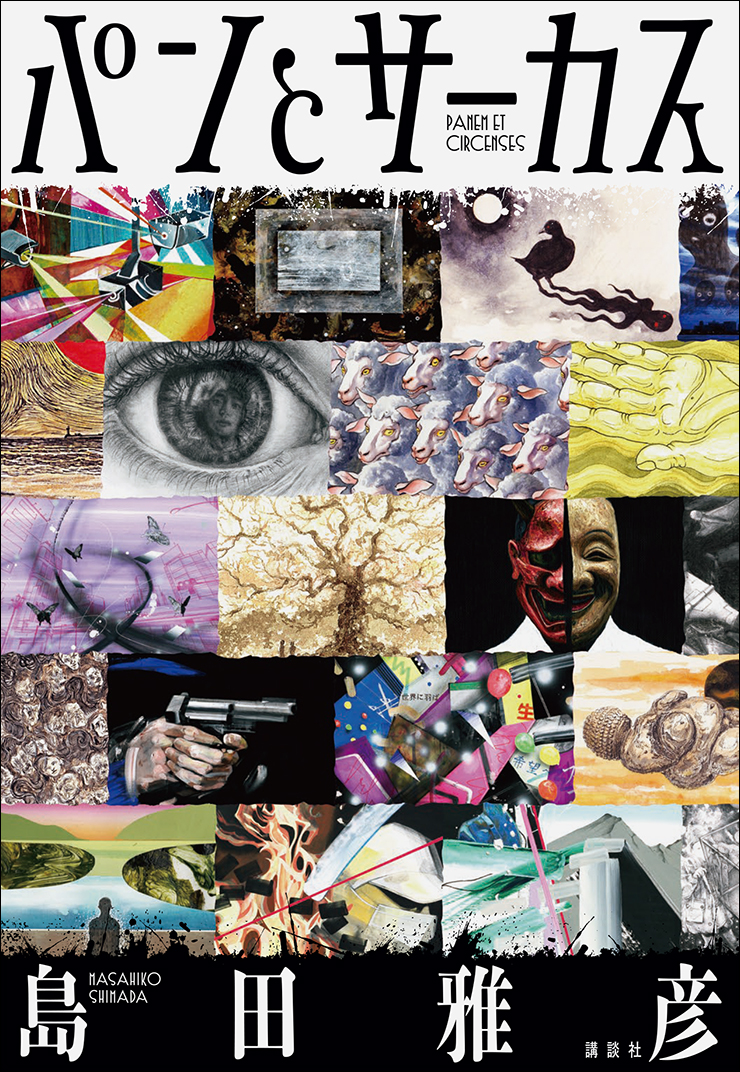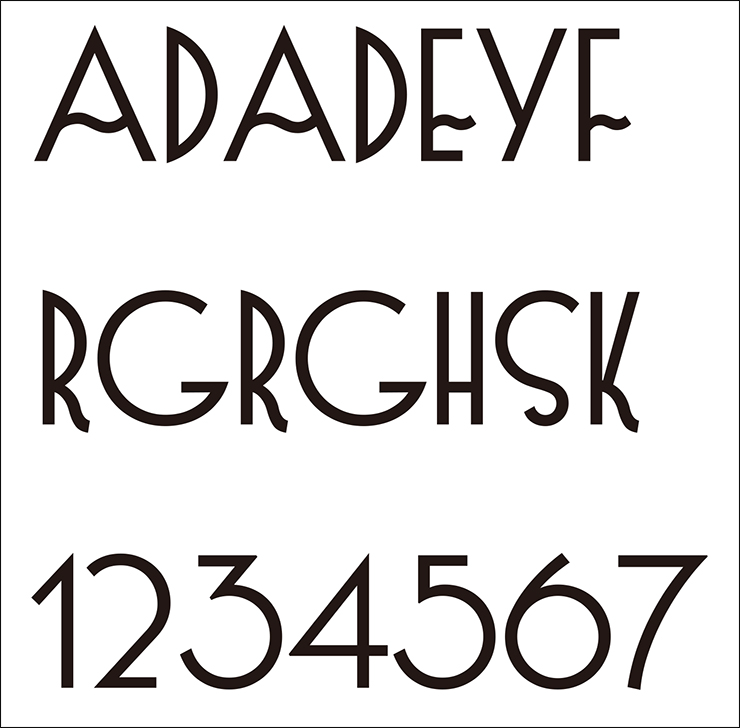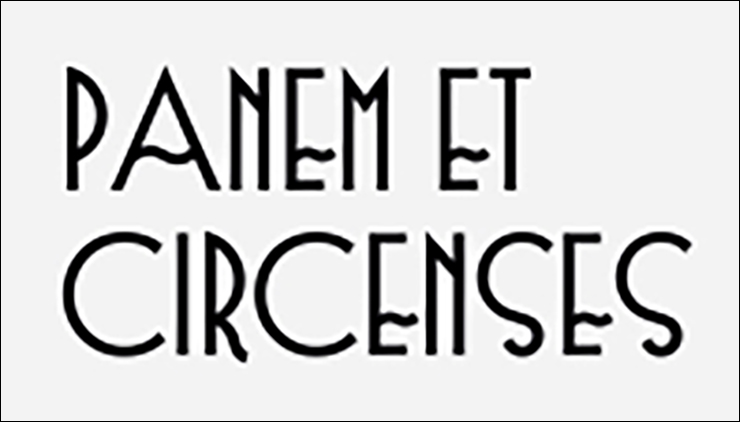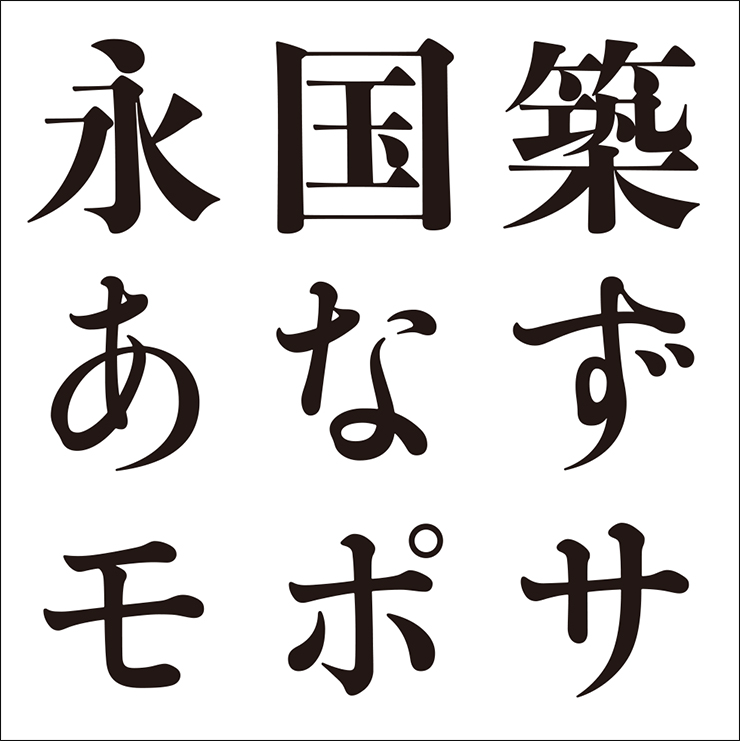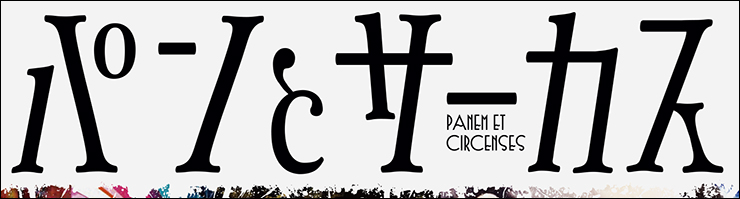
今回は書籍『パンとサーカス/島田雅彦』(講談社)の使用フォントについて、ブックデザインを手がけた川名潤さんに取材。特徴的なタイトル文字などの制作過程に迫ります。
装飾的な文字でタイトルが想起させる娯楽性や猥雑さを表現
不正隠蔽の犠牲となった父の復讐を果たすため米国留学を経てCIAエージェントとなった男が、日米両政府の表と裏を巧みに欺いて日本国民のかたきをとる姿を、現実の世界情勢を織り交ぜつつ壮大なスケールで描いたエンターテインメント巨編『パンとサーカス/島田雅彦』。2020年7月から翌年の8月にかけてブロック紙大手の朝刊に連載されたのち、加筆修正を経て単行本として刊行された。タイトルの『パンとサーカス』は、古代ローマの詩人ユウェナリスが当時の世相を揶揄した表現に由来しており、「政治的関心を失った民衆には食料(パン)と見せ物(サーカス)を与えておけば支配はたやすい」の意。
表紙カバーでは、冒険やサスペンス、政治など、ジャンルの枠を超えた作品世界が、欧文書体のエレメントをベースにした装飾的なタイトルロゴや、さまざまな画風の作品をモザイク状に配置したメインビジュアルなどで表現されている。デザイナーの川名潤さんによれば「連載時に掲載されたアーティストユニット『コントラ・ムンディ』による挿画の熱量が高かったので、それをカラーでもう一度見せたいと思いました。ひとつのジャンルにとらわれない作品世界や、タイトルの『サーカス』の語感が持つ娯楽性、猥雑さを、題字などの文字要素に反映するよう心がけました」とのことだ。
ちなみにアーティスト名の「コントラ・ムンディ(『世界の敵』を意味するラテン語)」は作中に登場する秘密サークルの名称から取られている。また本書の装丁者名も、作中に登場するデザイナー「大鴉ノア」の名でクレジットされている。
Font.01「オリジナル」
欧文書体のエレメントをもとに作り起こした文字で印象的に
メインタイトル「パンとサーカス」部分は、作品の内容や「サーカス」という言葉が持つイメージに合わせて作り起こされたオリジナルの文字。表情豊かなセリフ体「Plantagenet Cherokee」(Tiro Typeworks)など3種類ほどの欧文書体のエレメントをもとに制作された。書体見本はメインで使用された「Plantagenet Cherokee」のもの。
川名さんによれば「タイトルはあくまで愚民政策の比喩表現で、小説自体はパンやサーカスとは関係ありません。ただ、サーカスという言葉の語感が持つ娯楽性や猥雑さは作品の内容に通じるところがあるので、それを文字要素にも反映するようにしました」とのこと。
Font.02「游築見出し明朝体」
金属活字がベースの伝統的な明朝体を選択
著者名部分は、大正時代の金属活字をもとに制作された見出し明朝体「游築見出し明朝体」(字游工房)に。ジャンルの境界を超えた作品の多様性を念頭に、タイトルロゴとはイメージが異なる伝統的な書体が選択された。幅狭のタイトル文字とのバランスを考慮して、75%ほど長体がかけられている。
Font.03「Sidewalk Cafe BF」
個性的な欧文書体で猥雑さを
タイトルや著者名の欧文部分は、1930年代のポスターの手書き文字をもとに開発された、波打つような横画や個性的なフォルムが印象的な「Sidewalk Cafe BF」(Bomparte's Fonts)に。タイトルの語感が持つ娯楽性や猥雑な感じを表現するため、他の文字要素とは異なる雰囲気を持つカジュアルな書体が選択されている。